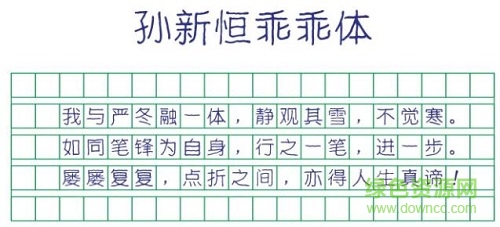
孫新恒乖乖體字體
孫新恒乖乖體是一款硬筆手寫動漫字體,整個字體看上去呈現(xiàn)一種波浪形,非常有特色,適合用來進行藝術(shù)創(chuàng)作!有需要的朋友歡迎下載使用!
孫新恒乖乖體是一款帶有童趣的學生時代的手寫字體。其字體不拘不束,隨心隨性,可愛可親,靈動時尚,使人勾起中小學時期的回憶。